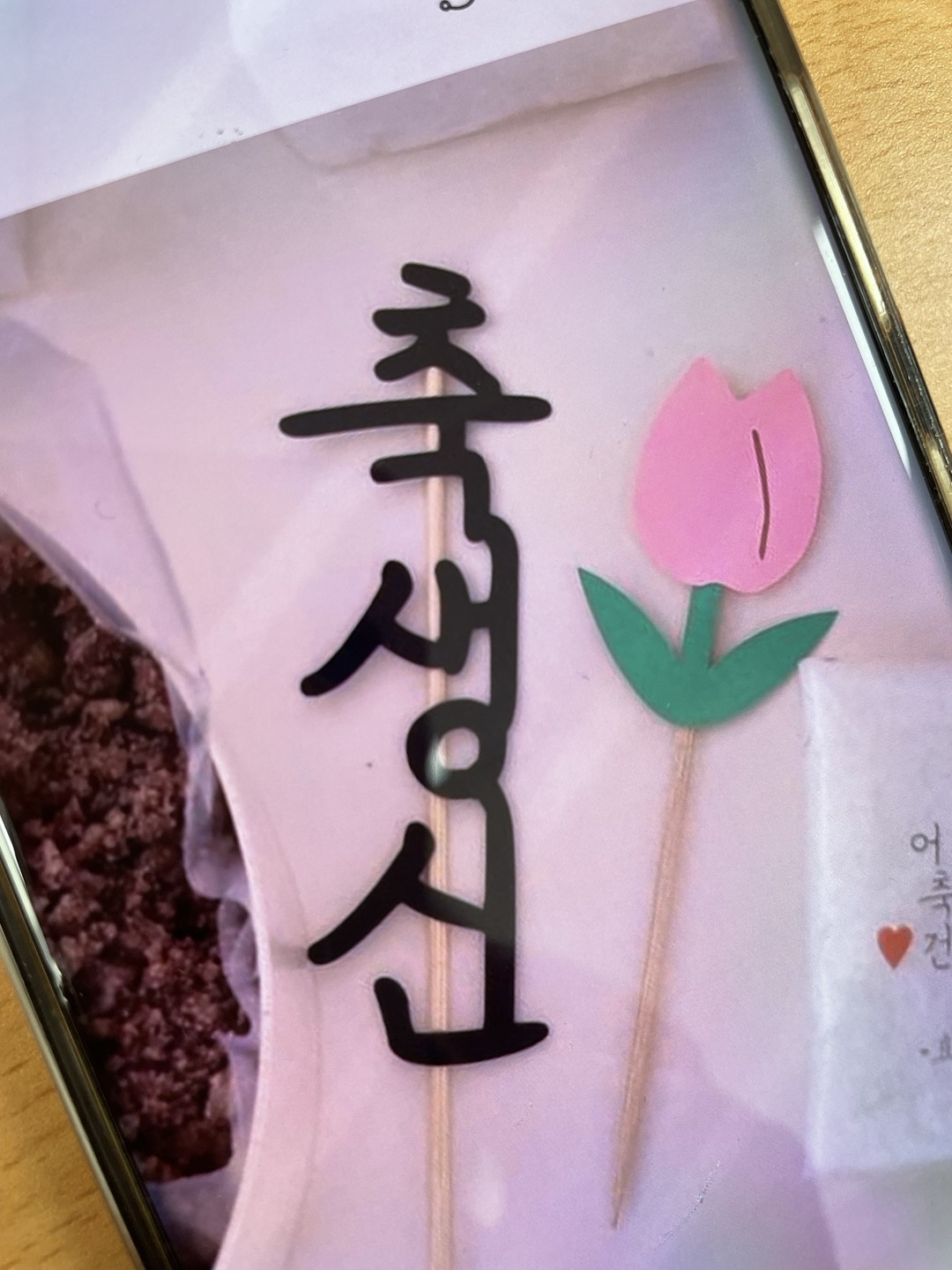
폰트 문의 드립니다. hen*** 2022.11.24 아무리 찾아도 안나와서 여기에 문의 드립니다. 토퍼 제작으로 글씨를 약간 수정한것 같기도 한데 연결부분을 자르고 해도 잘 안나오네요. 도와주세요~~!! 댓글 0 등록 오타대마왕 문체부 쓰기 정체를 세로로 쓰고 두껍게 한다음 토퍼로 쓸려고 자소를 연결한것 같아요. 2022-11-24 답글 달기 댓글 더보기 쉽고 빠르게 가장 비슷한 폰트를 알고 싶다면? 이미지로 검색하기
문체부 쓰기 정체를 세로로 쓰고 두껍게 한다음 토퍼로 쓸려고 자소를 연결한것 같아요.